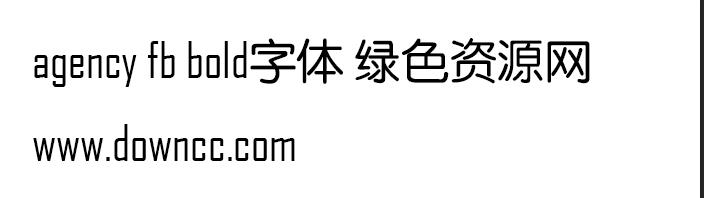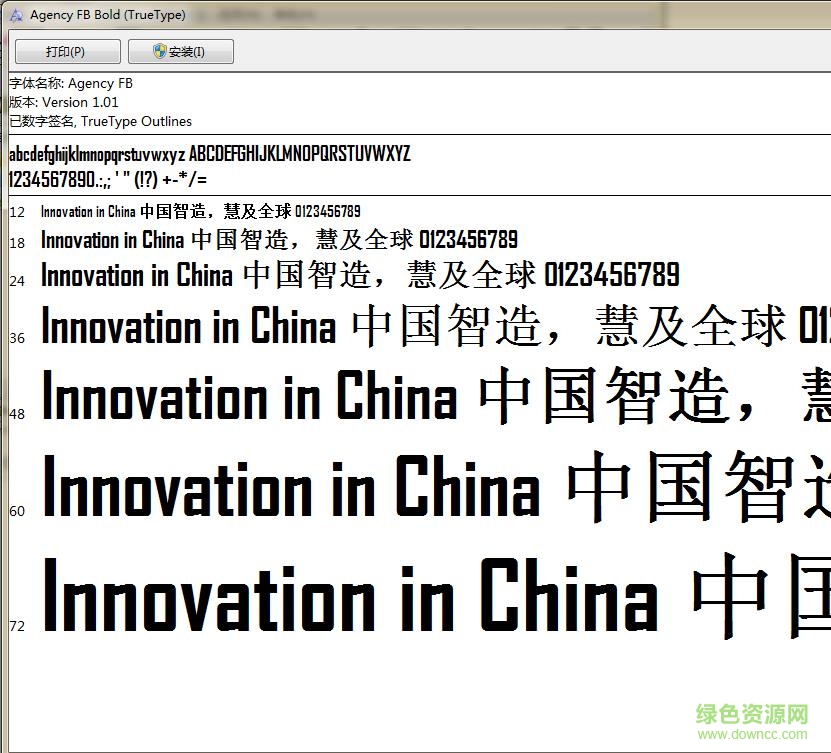
agency fb bold字體ttf是一款加粗型的英文字體,讓你在英文的書寫以及制作過程中能夠獲得更加不錯的體驗,其內的字體看起來就像一個個規(guī)整的方形,讓你擁有全新的視覺體驗,快來綠色資源網(wǎng)下載吧!
這款字體在英文字體中時長出現(xiàn),一款運用的比較廣泛的字體樣式,眾多外國用戶們通過使用這款自己進行藝術字創(chuàng)作,獲得了十分不錯的視覺成效!